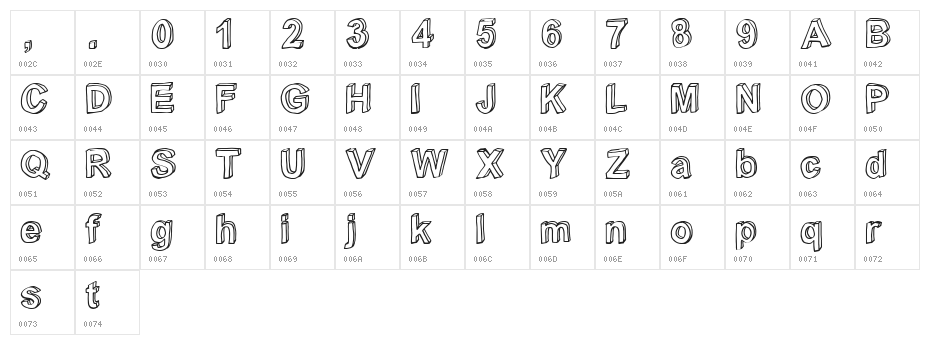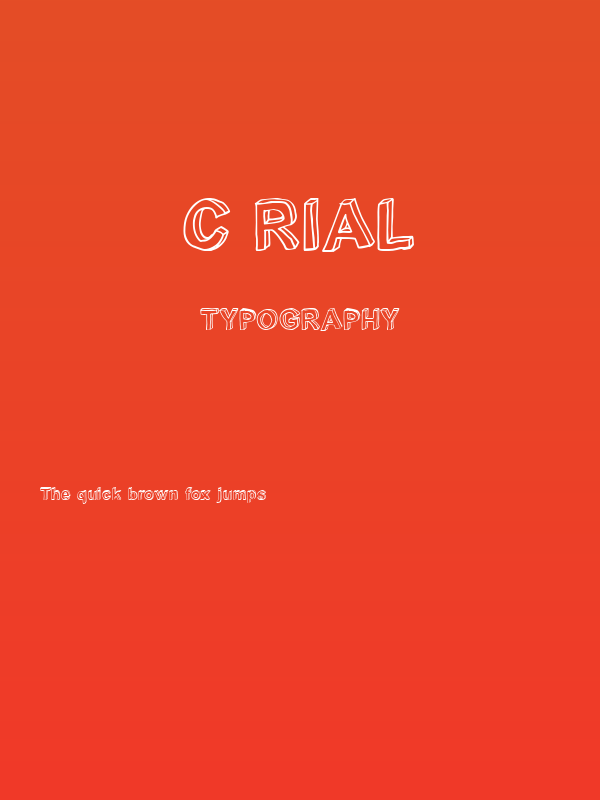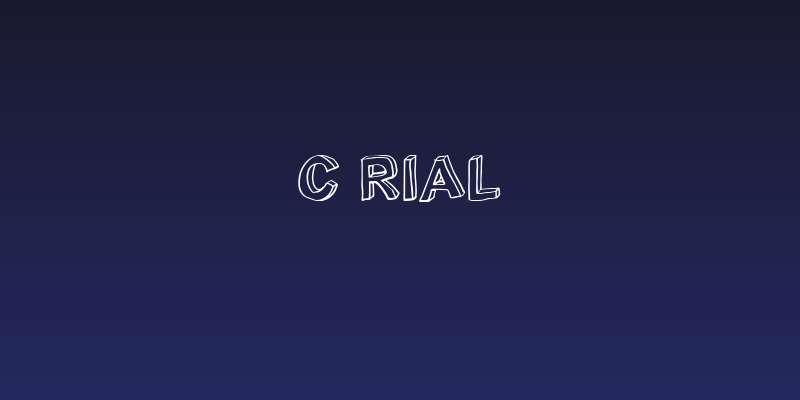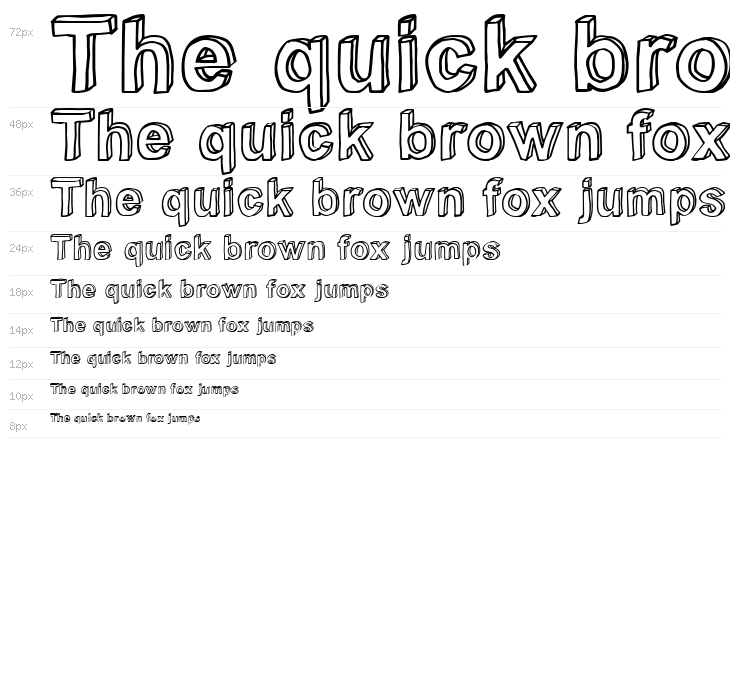
C rial Font
| Stile generale | Playful, Quirky, Fun |
| Caso d'uso | Headlines, Posters, Branding |
| Progetti proposti | Ideal for posters, children's books, comic strips, and playful branding projects. |